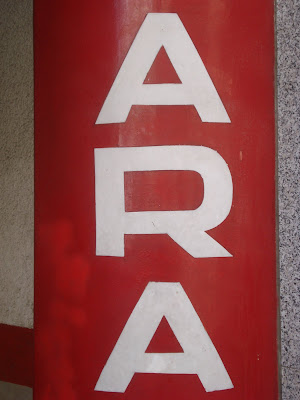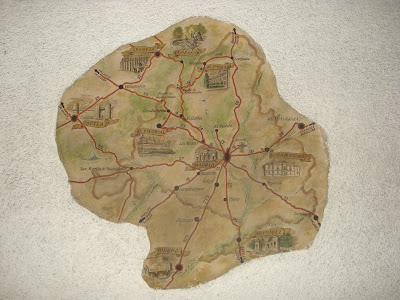
Garaje Paso
En Ponzano 54 (antiguo 52).
Las fotos inferiores reproducen los mapas pintados en las paredes de entrada al garaje: el de Madrid (situado a la derecha) y el de la entonces provincia y hoy comunidad (a la izda.), con sus principales carreteras.
En el mapa de Madrid se distingue claramente, al norte de la ciudad, el estadio Santiago Bernabéu, inaugurado en 1947.
Con este dato como referencia, y teniendo en cuenta el estilo, puede datarse el garaje a finales de esa década o inicios de la siguiente.
El Brillante
La cadena de bares-restaurantes El Brillante, de ambiente y espíritu tan madrileños, es conocida sobre todo por sus bocatas de calamares; su local más conocido es el de la glorieta de Atocha.
Esta sucursal de Eloy Gonzalo 14 fue en realidad la primera en abrir (en 1952, como informa un cartel en su interior), y proyecta su gráfica a la calle mediante diversos soportes, en una mezcolanza abigarrada y pintoresca.
Del año de su inauguración son sin duda el rótulo en bronce sobre la claraboya de la puerta y los neones de colores de la fachada (ambas cosas las encontramos también en el establecimiento de Atocha que, aunque mucho más popular, abrió en 1961).
Como nota singular, el mural de hormigón en su fachada lateral a la calle del Cardenal Cisneros.
Fue seguramente añadido una o dos décadas más tarde, junto al panel de cerámica que lo rodea, en una exploración plástica de ambos materiales típica de los años 60 y 70.
Mantequería San Francisco
En Bailén 49.
Inaugurada en 1930, muestra en su fachada la letrería art decó característica de la época, casi idéntica a la reproducida en el cartel de la película de 1934 "Cautivo del deseo" (abajo).
La tipografía fue uno de los rasgos que definieron la exuberancia decó de los años 20 y 30 del siglo XX, tanto como las modas cubistas, el mobiliario aerodinámico, los rascacielos escalonados y los trasatlánticos de lujo.
Las fuentes art decó nacieron de la necesidad consciente de la sociedad de la época por ser moderna, y aun cuando sus creadores fracasaran en el intento, todavía hoy día resultan fascinantes y útiles, como hemos visto en la gráfica de los anuncios de Línea Directa o en los comerciales vintage de Schweppes para televisión.